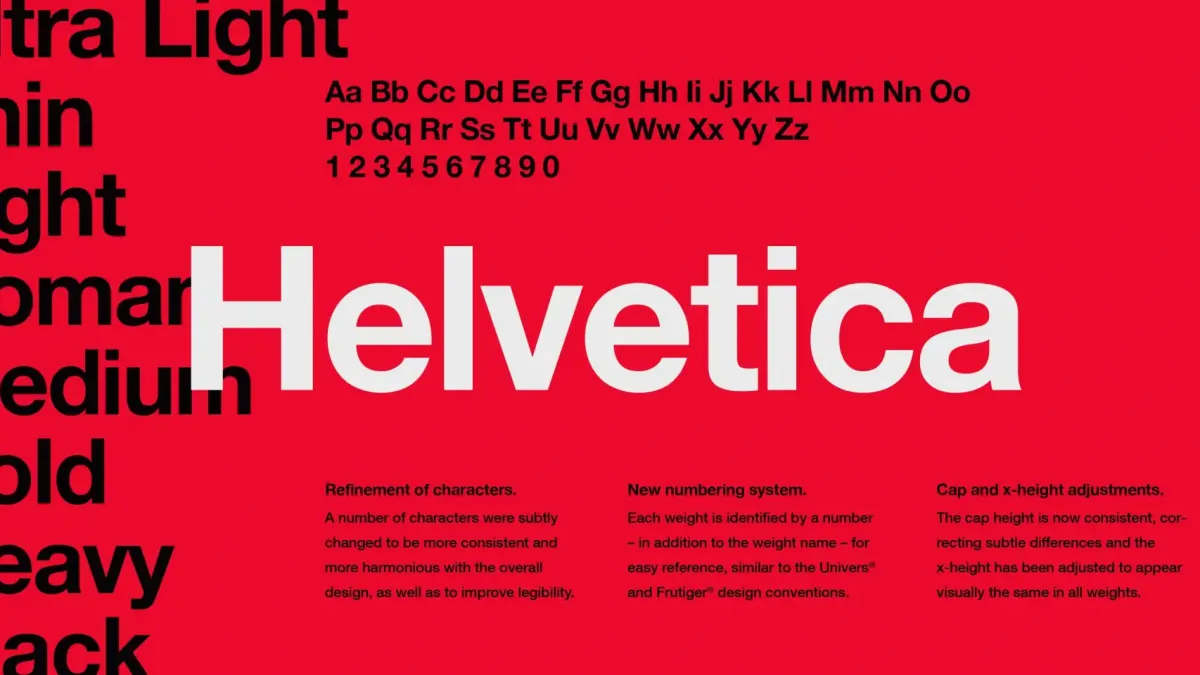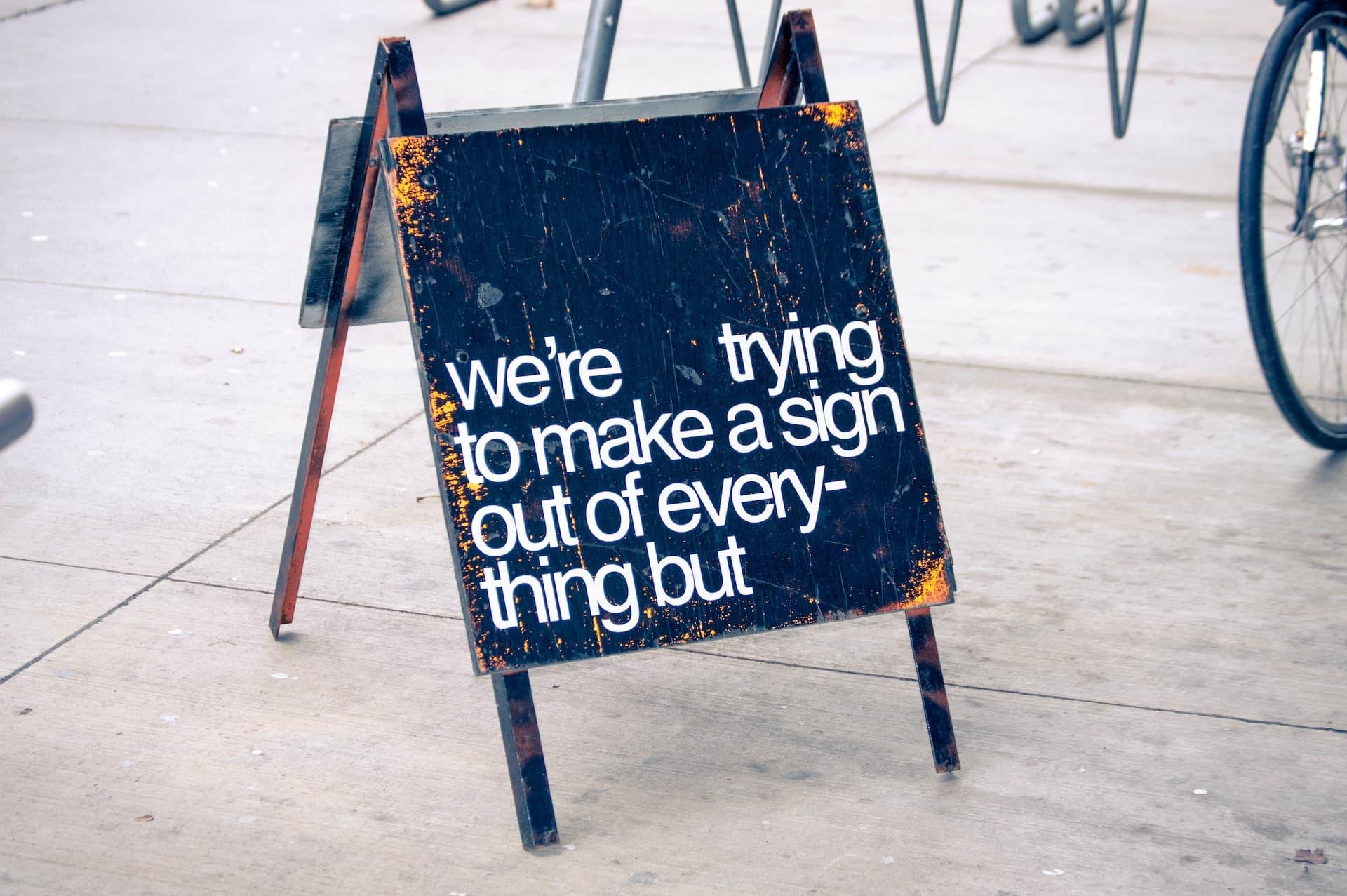
Police Helvetica, le culte de la grande dame suisse
En tant que maquettiste/graphiste on est tous les jours confronté à ces problèmes : Quelles typos pour ce projet ? Est-ce que celles-ci seront cohérentes avec l’émotion que je veux véhiculer ?
Voici le premier article d’une longue série qui va porter sur les choix typographiques d’un projet. Aujourd’hui il s’agit de la police Helvetica, la célèbre police d'écriture suisse.
Un mauvais choix de police d'écriture pourra s’avérer désastreux et rendre un projet fade et sans saveur. Notre oeil est habitué à certains codes visuels. Regardez cet exemple, chaque police traduit un message différent :
L'histoire de la police Helvetica (Familles des linéales)
La police Helvetica fut créée en 1957 à Bâle par Max Miedinger qui est alors employé par la fonderie typographique Haas.
Il dessina la police Helvetica dans un but bien précis : atteindre la simplicité absolue.
Elle devient rapidement l’emblème de la typographie suisse par sa logique, sa clarté et sa simplicité. Ses traits sont tout simplement une pure merveille. Parfaitement proportionnés, lisses et élégants.
Choisir cette typo est synonyme d’efficacité et de modernité. Elle se distingue aussi par sa complète neutralité, ce qui lui permet de se prêter à tous les usages.
Exemples d’utilisation de la police Helvetica
La police Helvetica est l’une des polices les plus utilisées au monde. On la retrouve partout. Dans les pubs, les menus, les signalisations routières et ferroviaires, et même dans le métro New-yorkais. Tout ou presque est écrit en Helvetica.
Depuis les années 70, les grands groupes l’utilisent dans leurs «corporate identity».
Le cas Arial
Quelques mots sur la police Arial, qui a été dessiné par Microsoft. En effet, la firme n’a pas voulu inclure la police Helvetica avec Windows pour des raisons financières. Or, son omnipresence la rendait obligatoire. Microsoft a donc déposé Arial, une police au dessin presque identique à celui de la police Helvetica (voici un petit test pour en avoir la preuve), comme mesure de réduction de coûts.
Arial ne jouit donc pas d’une bonne réputation auprès des professionnels du graphisme et de la typographie.
L’ironie du sort est que jusqu’en 2012, le logo de Microsoft était composé de la police Helvetica.
Pour résumer, la police Helvetica peut être utilisé en caractères de titrage ou de labeur court, car elle est très lisible malgré l’absence d’empattements.
La police Helvetica est une police caméléon, qui passe partout : son dessin intemporel (car n’étant pas synonyme d’une période historique) et son apparence de neutralité la rendent exploitable dans beaucoup de domaines. L’inconvénient à cela est qu’utiliser la police Helvetica ne renforcera pas votre message.